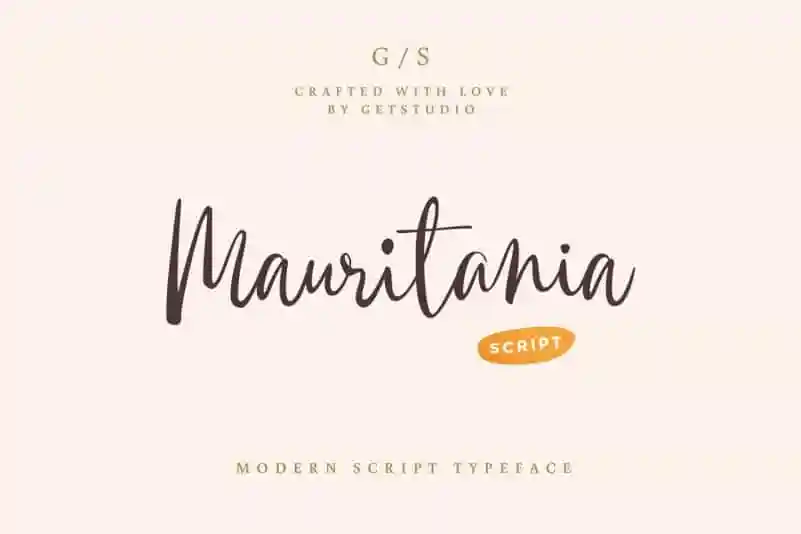
Mauritania Handwritten Font – Download Grátis
A Mauritania Handwritten Font é uma fonte escrita a mão que oferece um toque delicado e distinto, perfeita para quem busca transmitir mensagens inovadoras com um tom natural e autêntico. Criada pelo designer Hamilton da Get Studio, esta fonte script é ideal para aqueles que desejam adicionar um ar de elegância a suas criações gráficas sem perder seu charme pessoal. Com sua base de escrita em dança que oferece uma sensação única e moderna, a Mauritania Handwritten Font permite que você envolva seus designs com uma mensagem corajosa que mantém o sentimento inabalável da autenticidade. Perfeita para aplicar em nomes ou pequenos detalhes em sua próxima peça de design, esta fonte certamente deixará seu trabalho ainda mais impactante e único. A Mauritania Handwritten Font é perfeitamente adequada para designers que buscam incorporar elementos delicados e sofisticados em suas criações. Composta com cuidado para capturar a essência da escrita à mão, esta fonte oferece uma maneira lúdica de expressar sua personalidade no design gráfico.